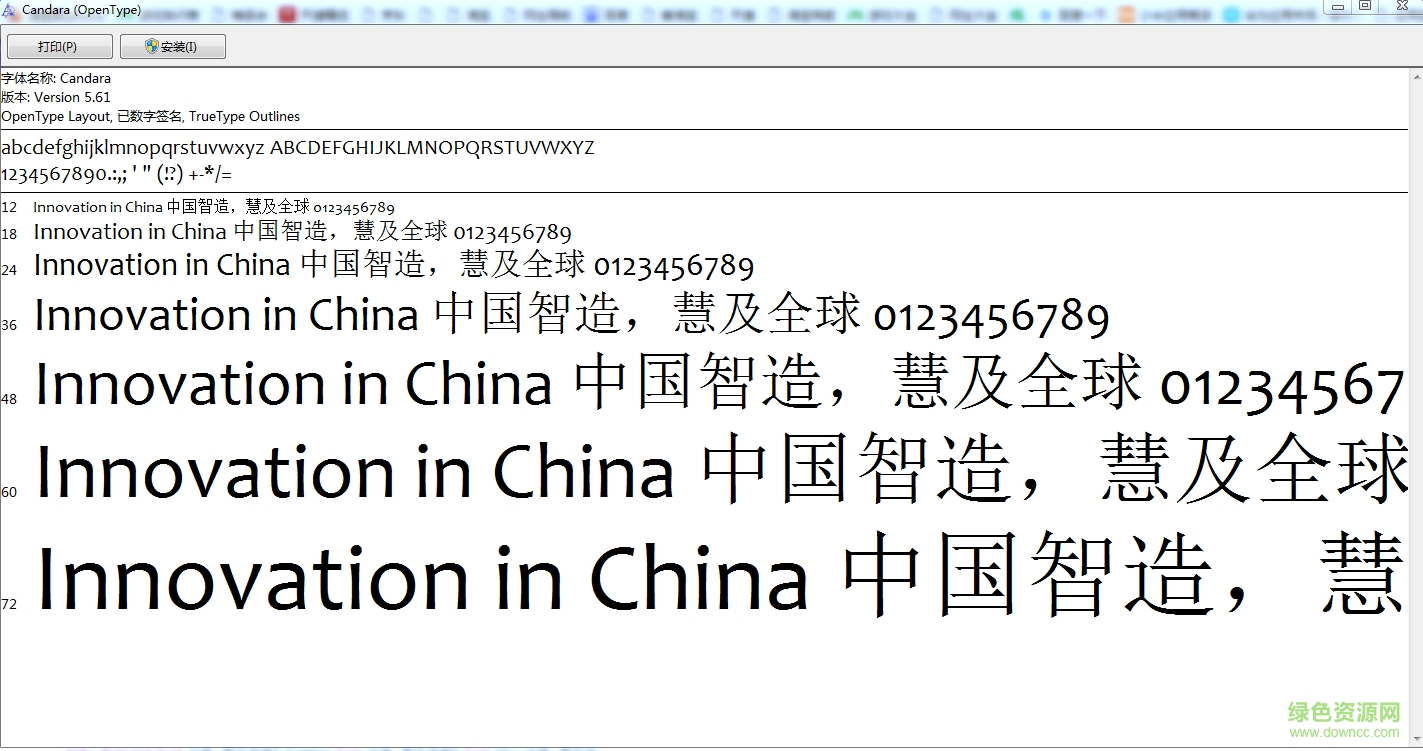
candara字體包是一套免費英文無襯線字體,筆畫干凈毫無多余點綴,字形典雅端莊,常用于品牌設(shè)計或海報宣傳方面,歡迎大家在綠色資源網(wǎng)下載!
無襯線體(Sans-serif)專指西文中沒有襯線的字體,與漢字字體中的黑體相對應(yīng)。與襯線字體相反,該類字體通常是機械的和統(tǒng)一線條的,它們往往擁有相同的曲率,筆直的線條,銳利的轉(zhuǎn)角。